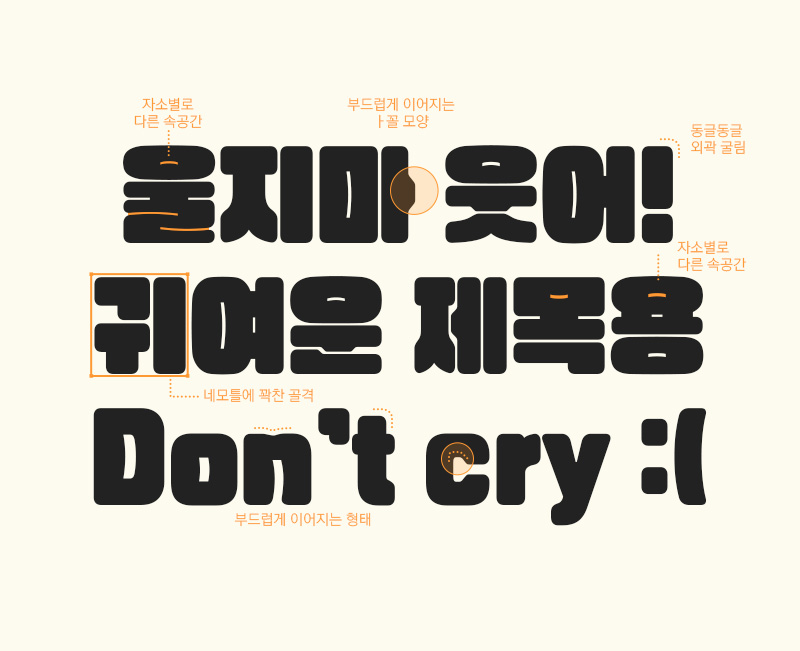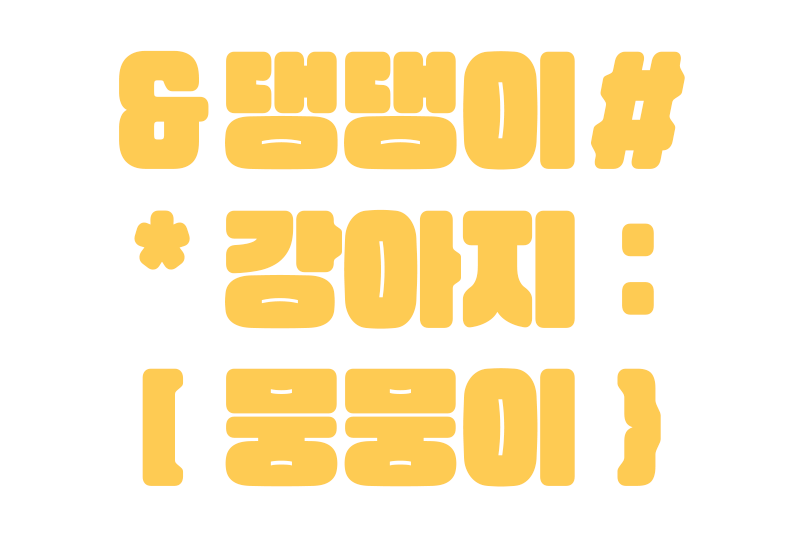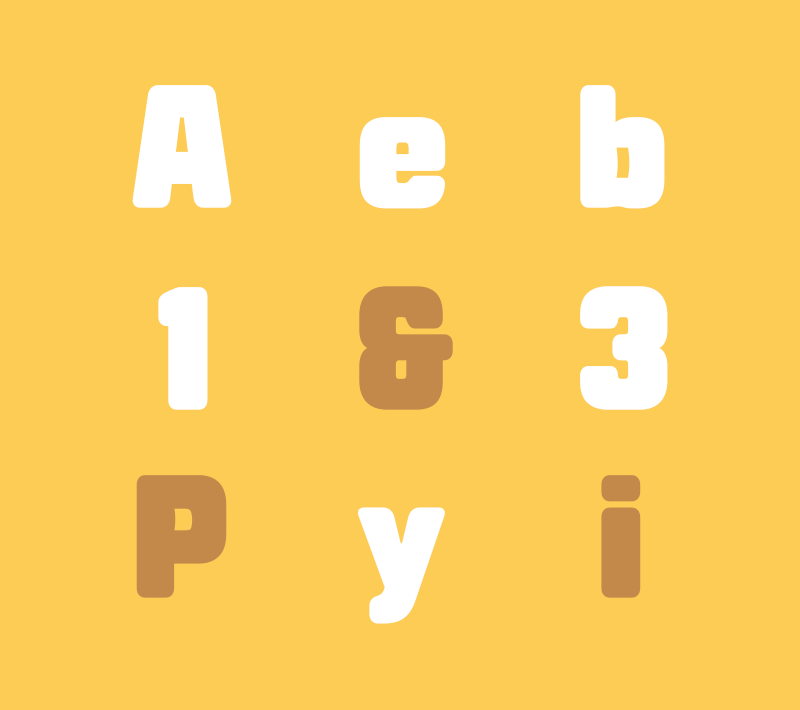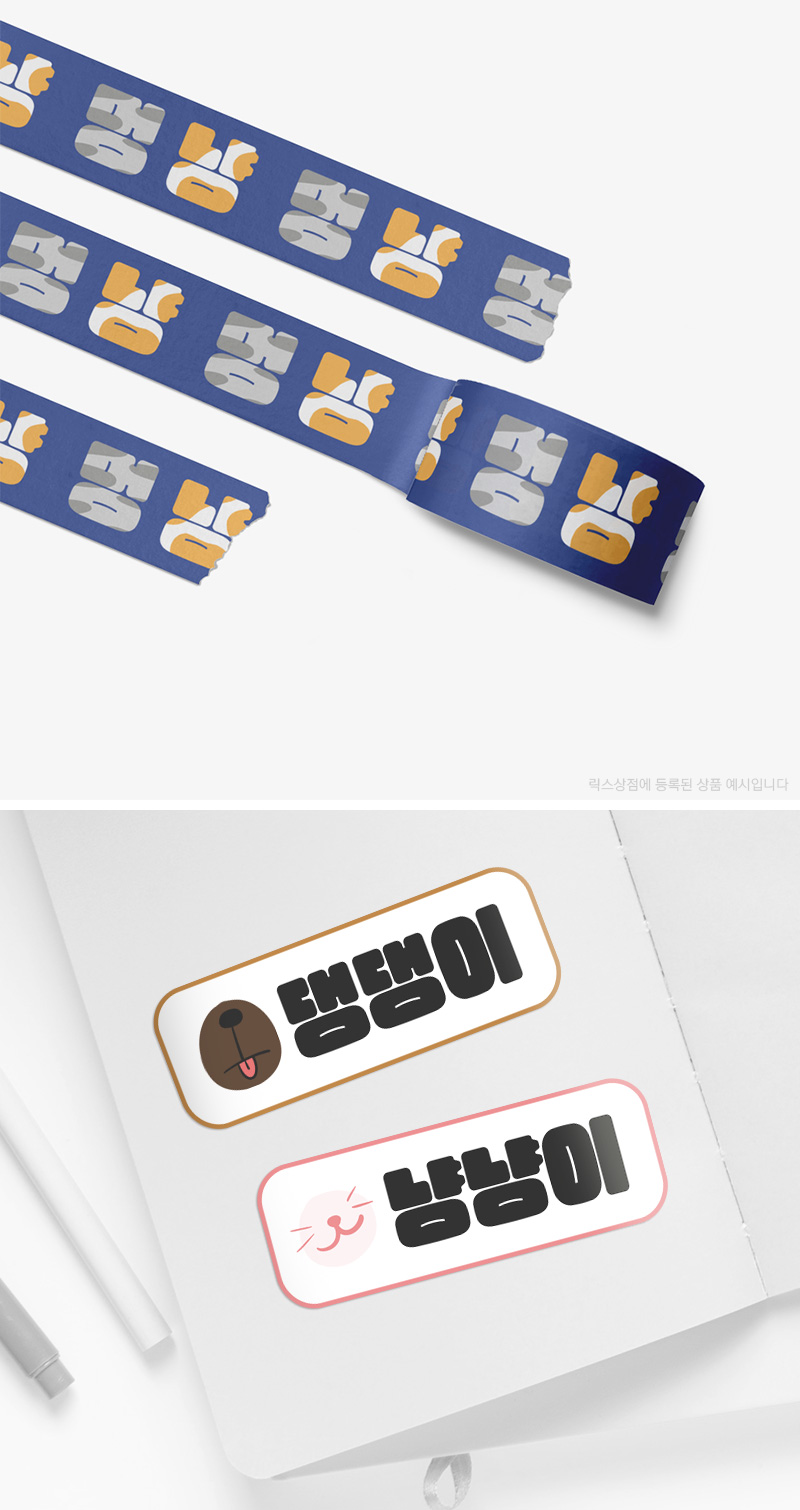
RixInooAriDuri
1 Style - Regular글자 속공간에 재미를 주어 다양한 표정을 담은 글꼴입니다.
댕댕이를 닮은 동글동글한 형태와 부드러운 굴림이 귀여운 인상을 줍니다.
네모꼴에 꽉 찬 골격과 두꺼운 획으로 주목도가 높은 제목용 서체입니다.
| FontFamily | Rix이누아리두리 / RixInooAriDuri |
| Design | Lee Ji Yoon |
| Direction | Park Yong-rak |